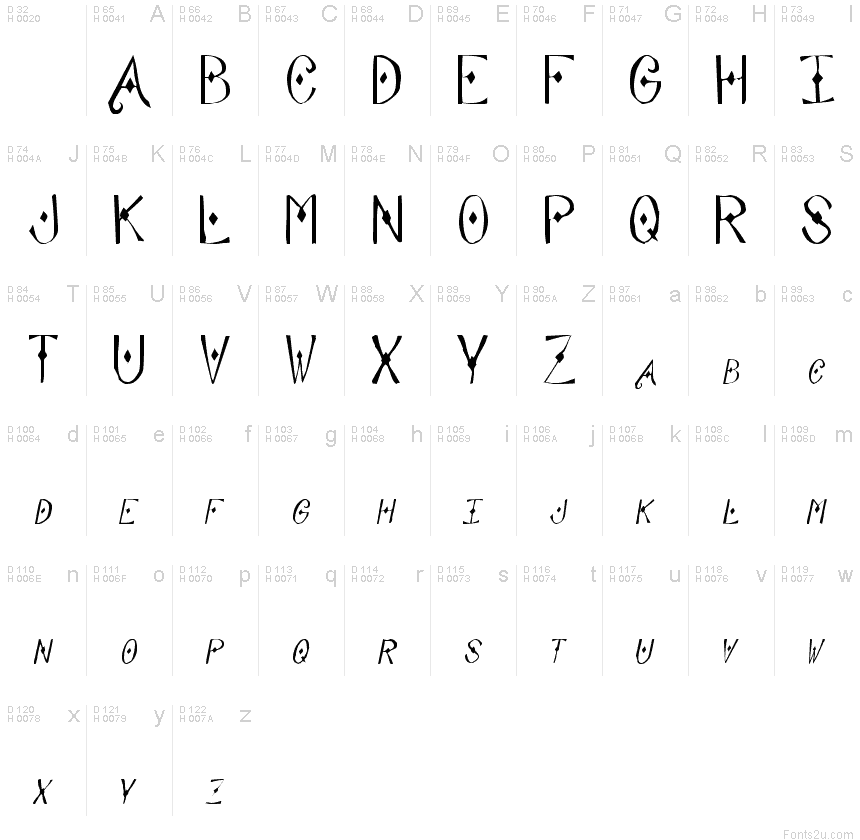
Abode هو خط عرض جذاب يتميز بجماليات مشوهة ومميزة. تلفت حروفه غير المنتظمة والعضوية الأنظار على الفور، مما يضفي لمسة من الغموض والتفرد.
بفضل طبيعته المرحة والجريئة، يُعد هذا الخط مناسباً لمجموعة متنوعة من تطبيقات التصميم، بدءاً من العناوين اللافتة للنظر وصولاً إلى العلامات التجارية وتصاميم التغليف ذات التأثير القوي. كما تتيح تعدد استخداماته للمصممين توظيف طابعه الفريد لإنشاء تكوينات بصرية مذهلة تترك انطباعاً لا يُنسى.
يُعد أسلوب Abode غير التقليدي خياراً مثالياً للمصممين الذين يسعون لإضافة لمسة من الشخصية والتميز إلى أعمالهم.